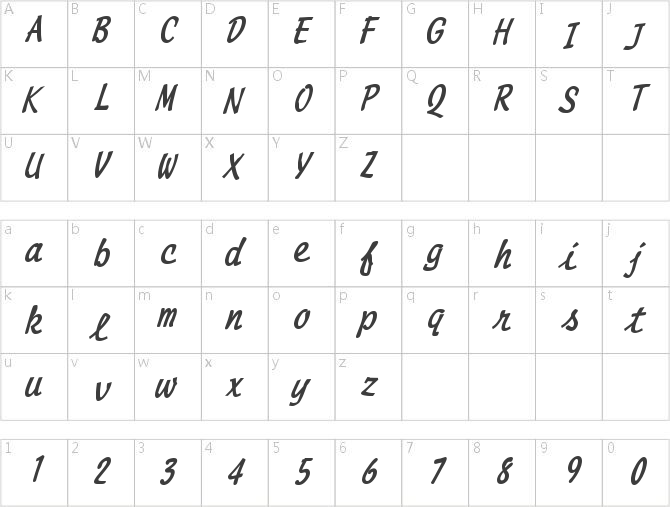
Manuscript-Condensed-BoldItalic 詳情頁(yè)
Manuscript-Condensed-BoldItalic字體字庫(kù)是一款讓人賞心悅目、百看不厭的英文字體,適合各類廣告和產(chǎn)品包裝設(shè)計(jì)應(yīng)用,字體大小0.07MB,格式為ttf字體,上傳用戶是華大文化傳媒,作者/版權(quán)方為未知